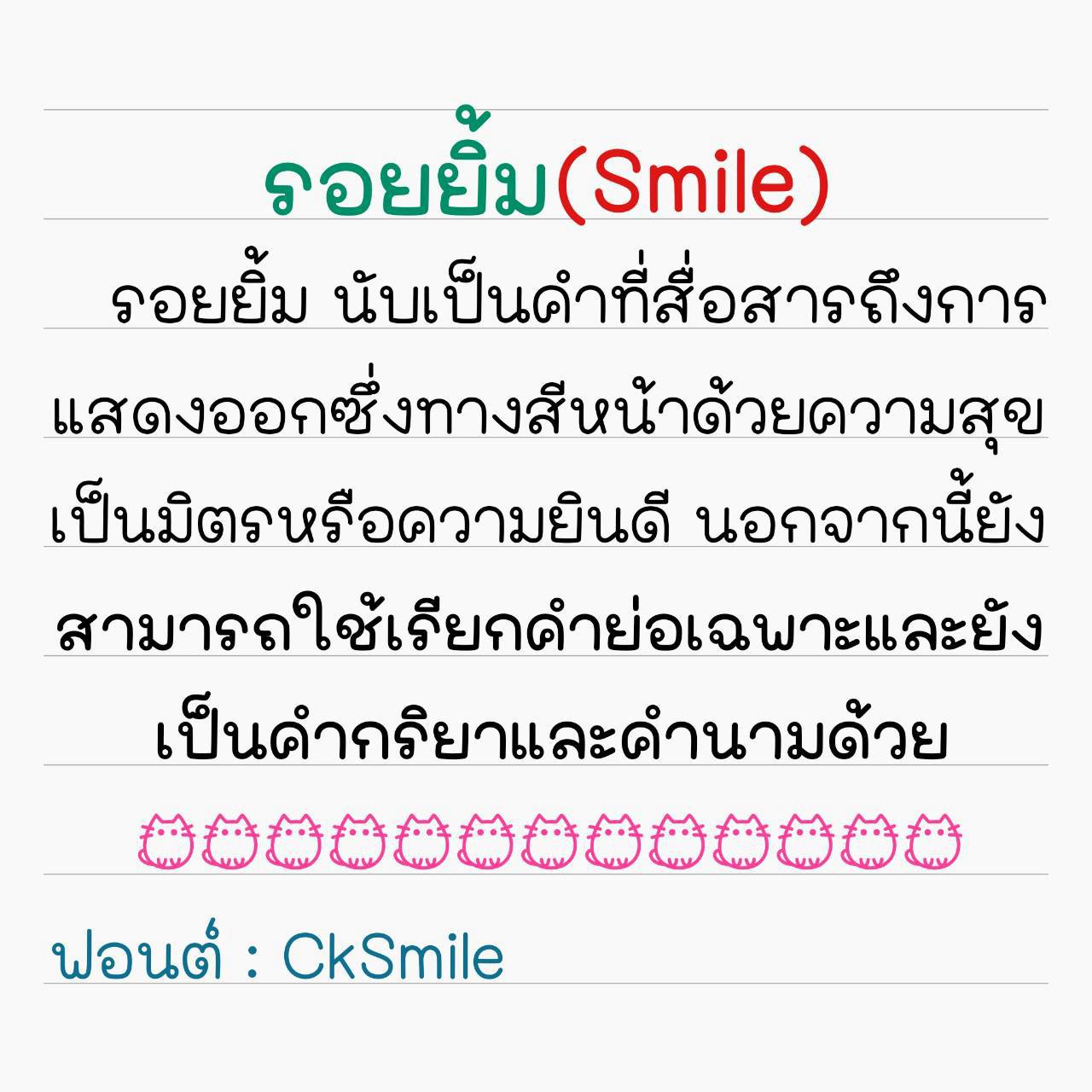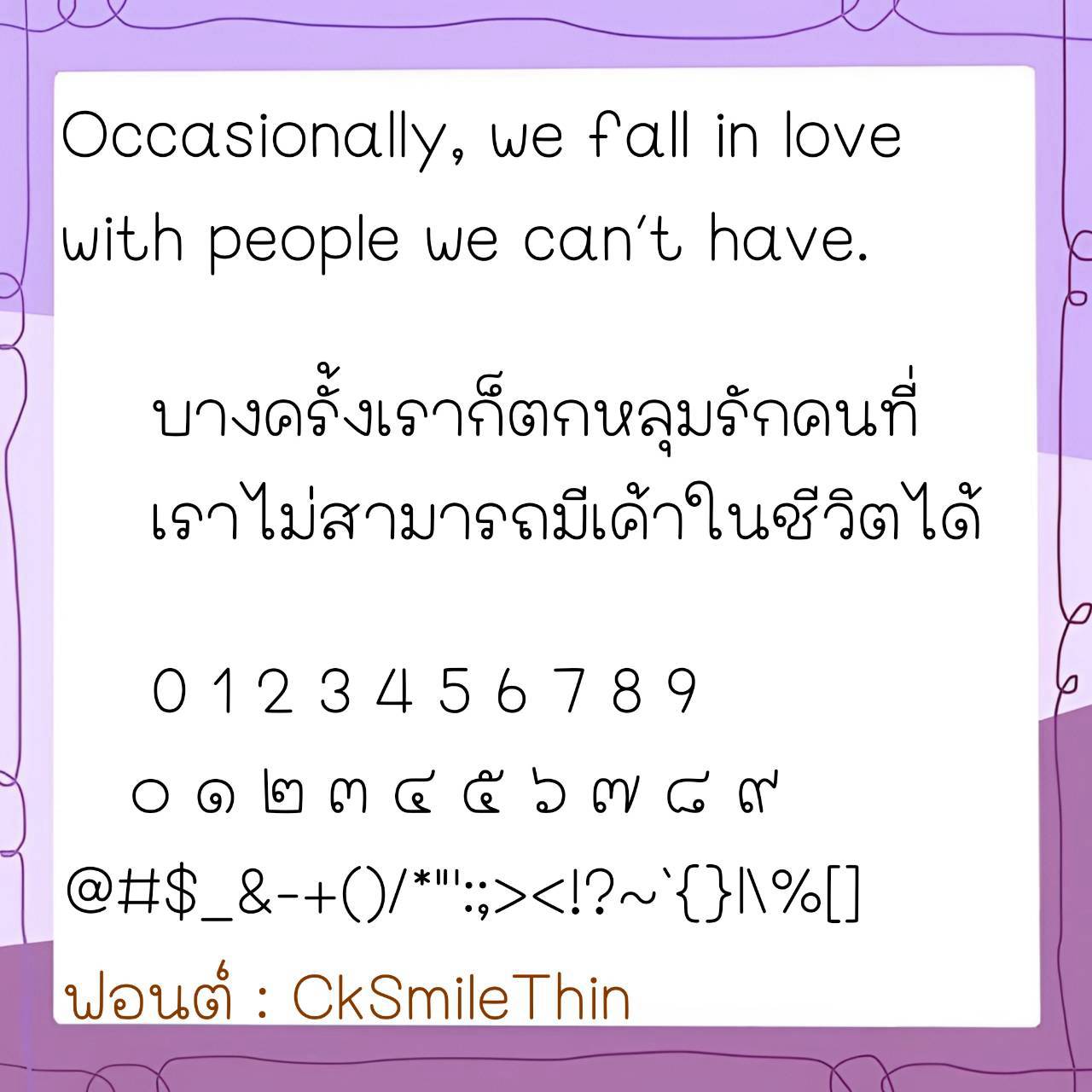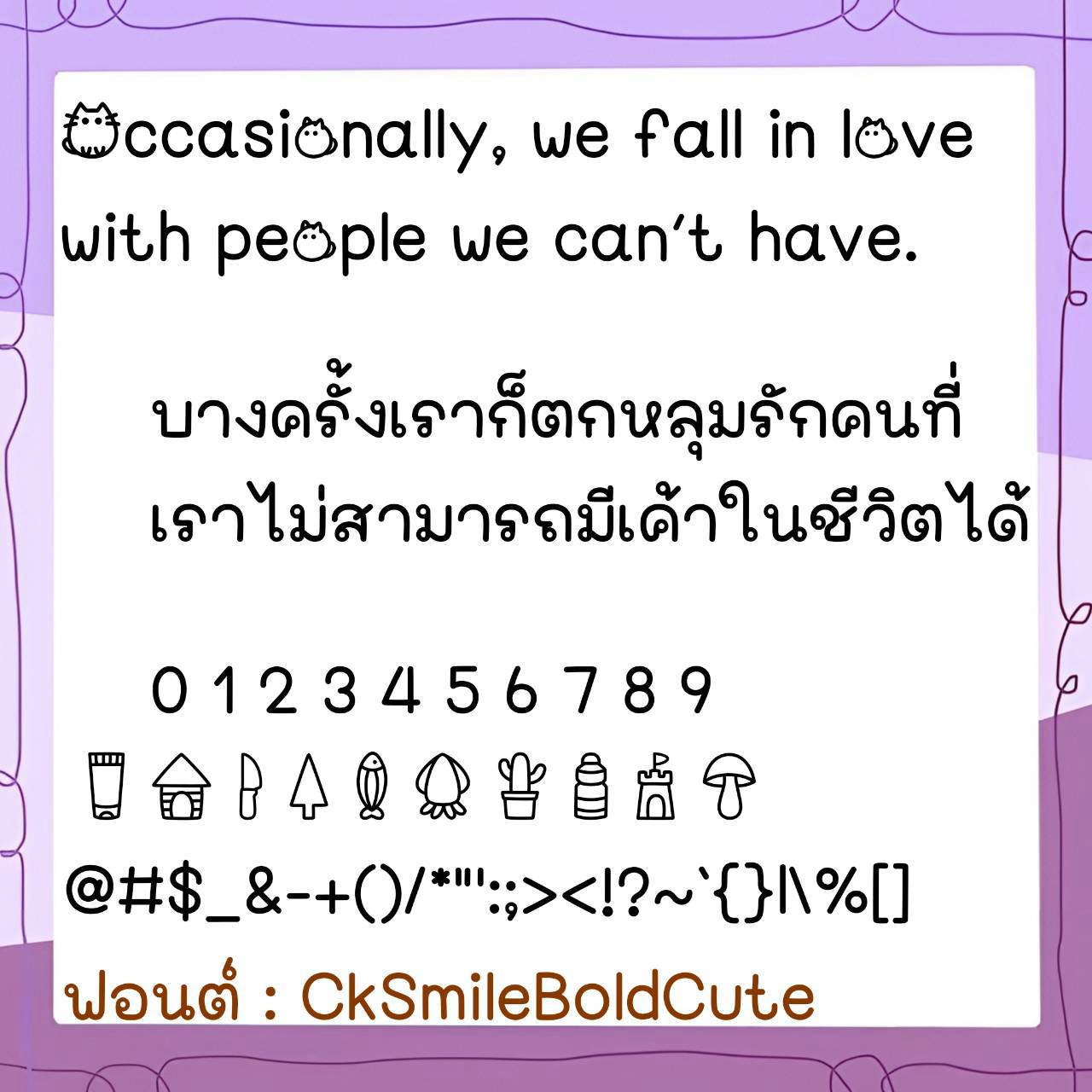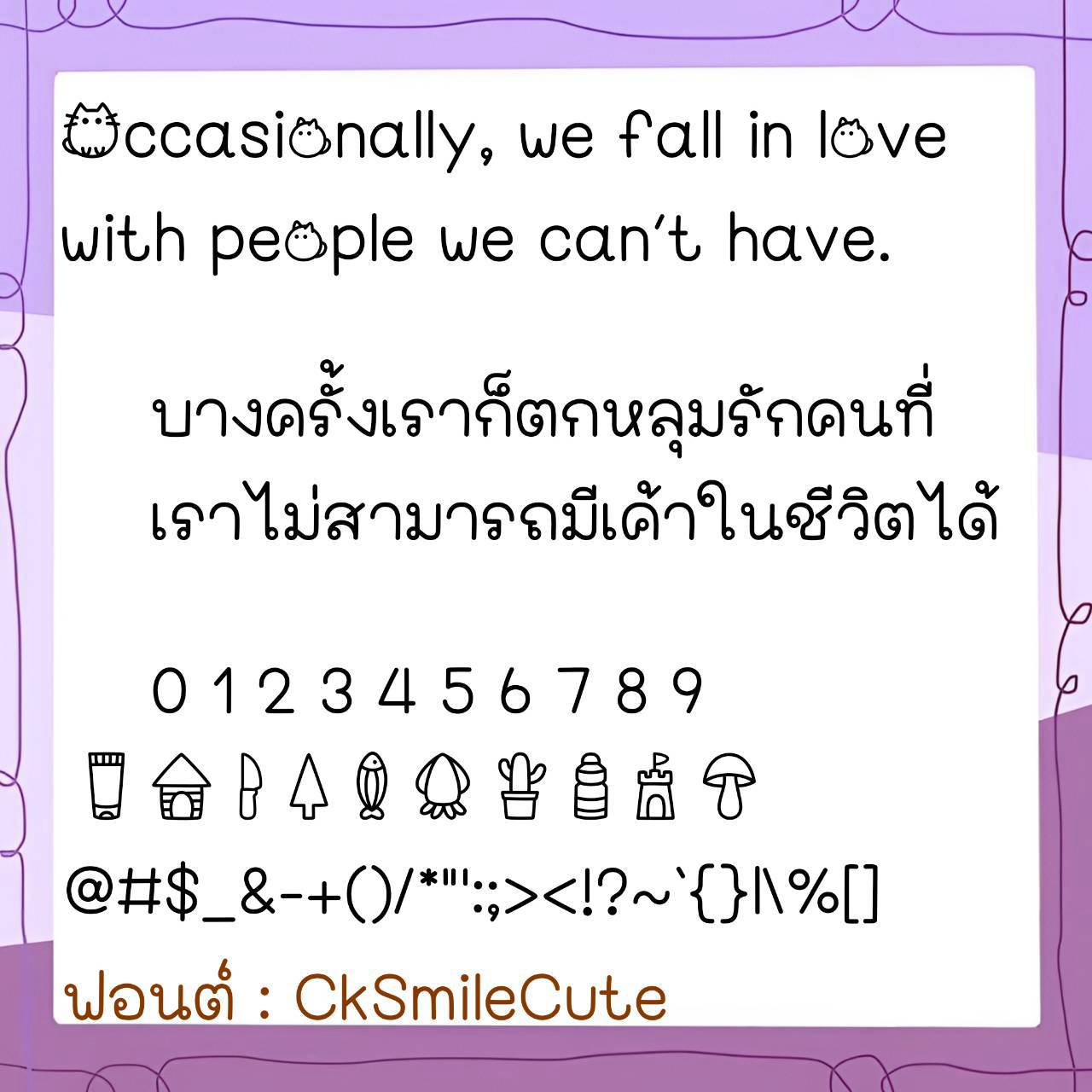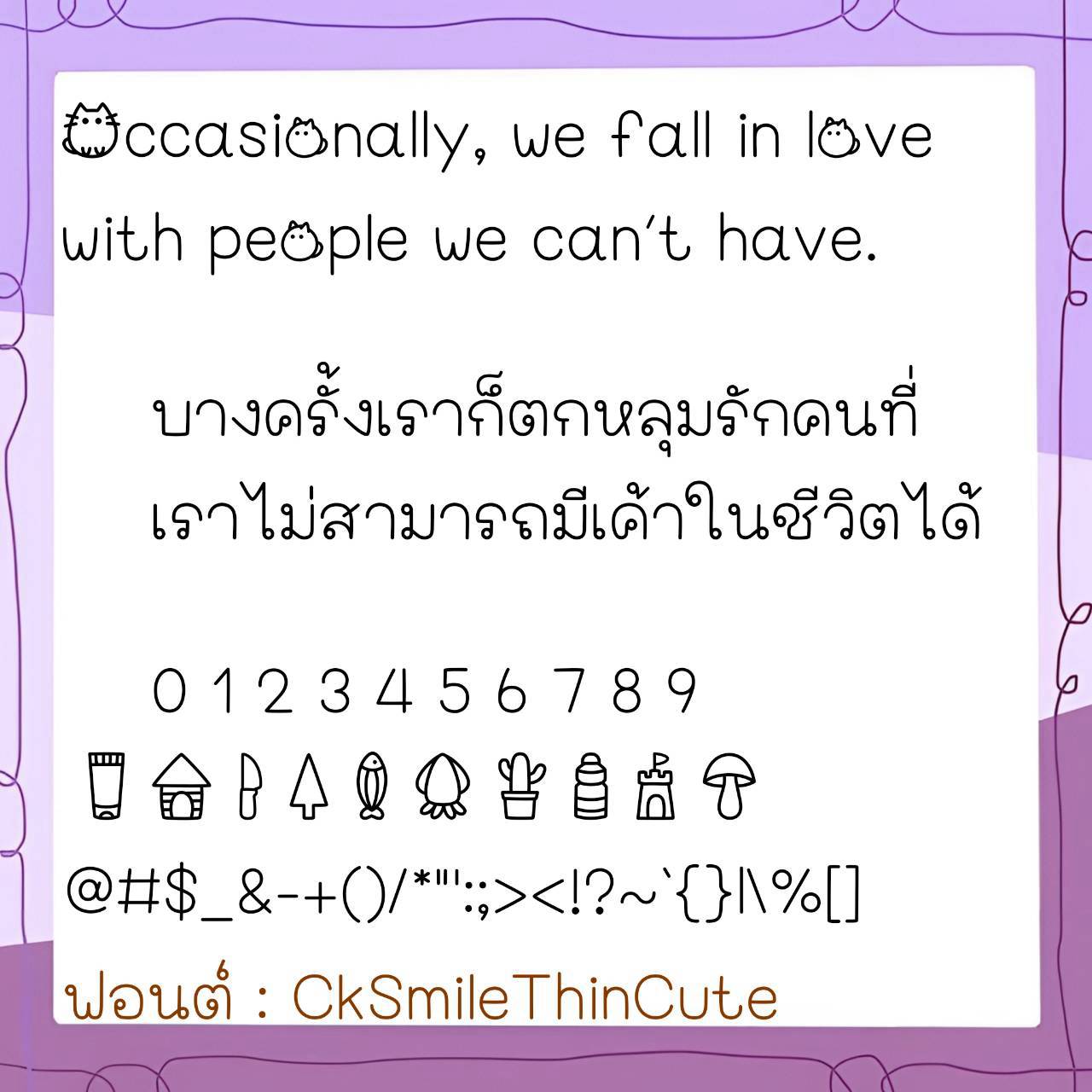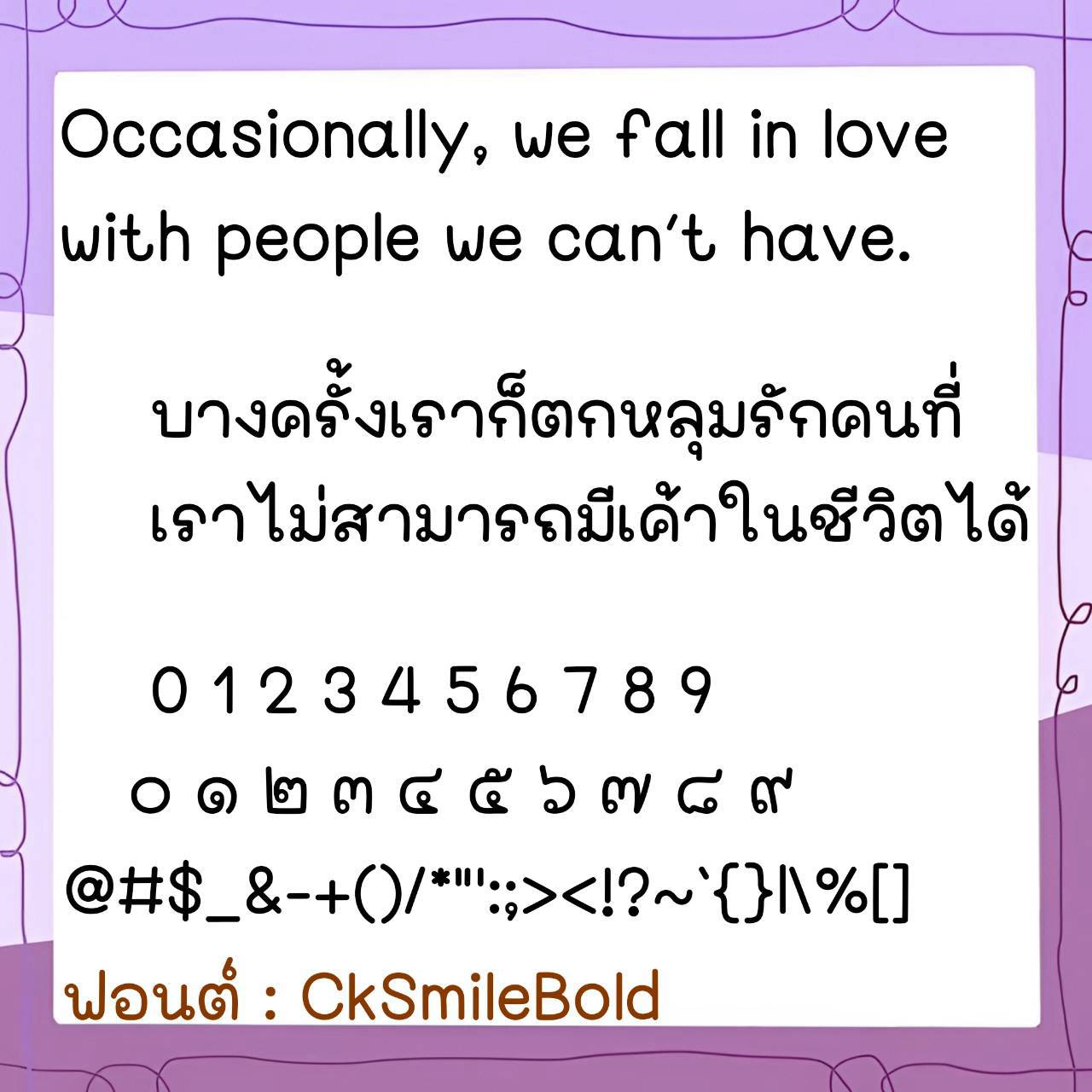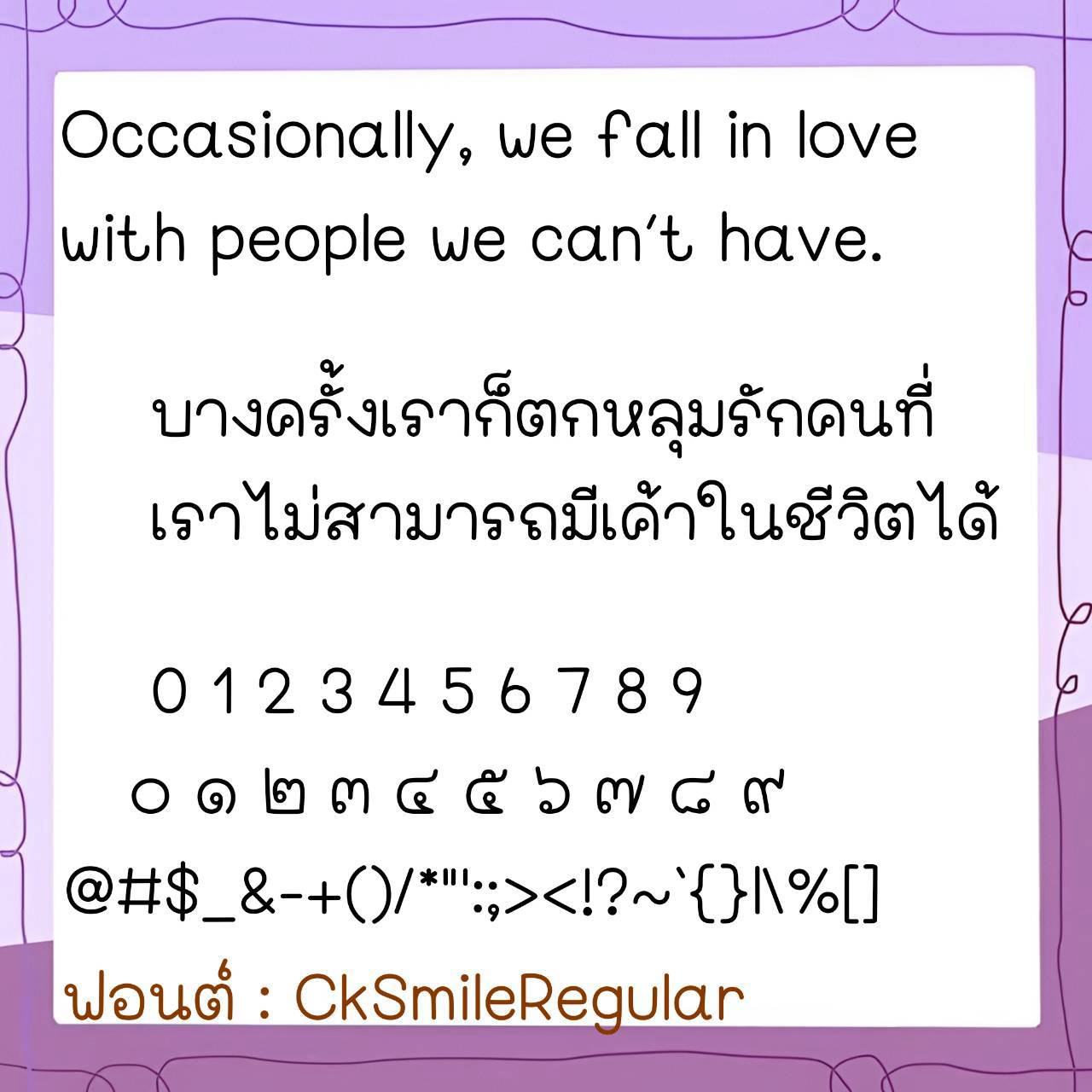
Font CkSmile
ชื่อสินค้า : Font CkSmile 💙
🔸 ฟอนต์ลายมือแนวน่ารัก หัวเล็กตัวอ้วนกลม เน้นอ่านง่ายดีต่อสายตา และยังมีไฟล์อิโมจิน่ารักๆที่ใช้แทนเลขไทยให้ด้วยค่ะ 🥰💙
🔹 A cute handwritten font with small, chubby characters, designed for easy reading and comfortable on the eyes. It also includes cute emoji files to replace Thai numerals. 🥰💙